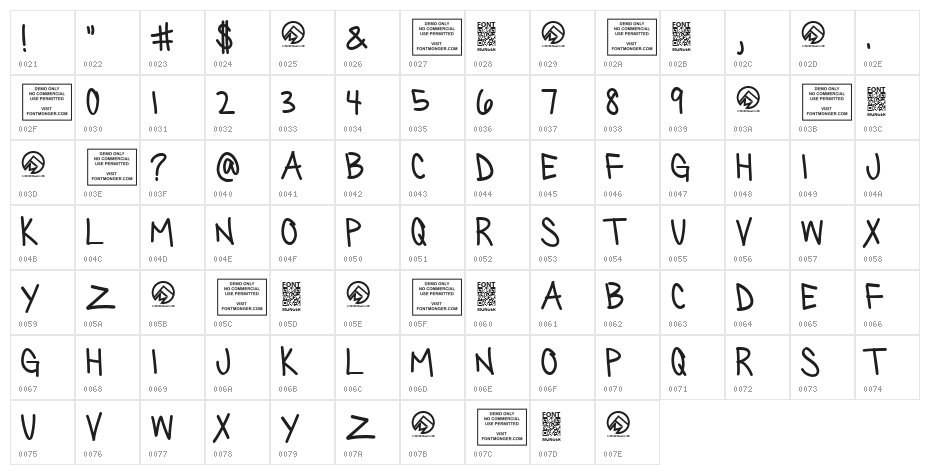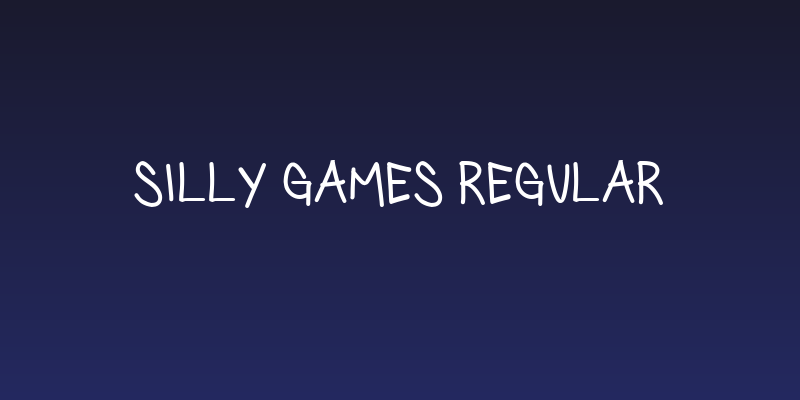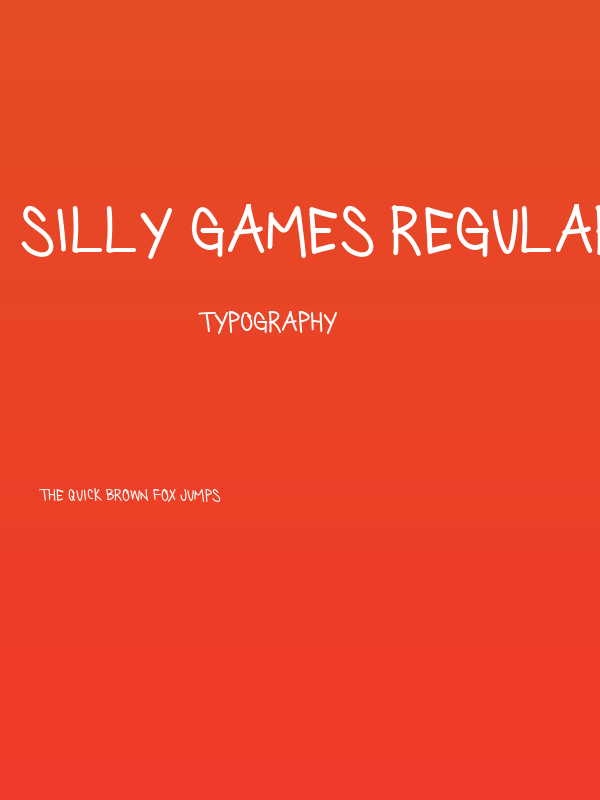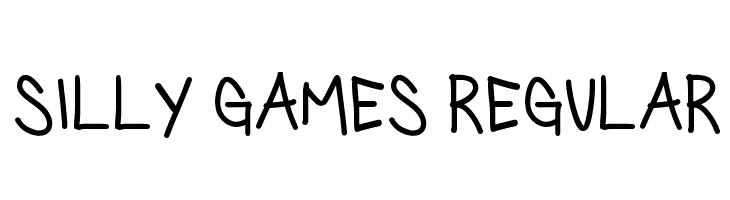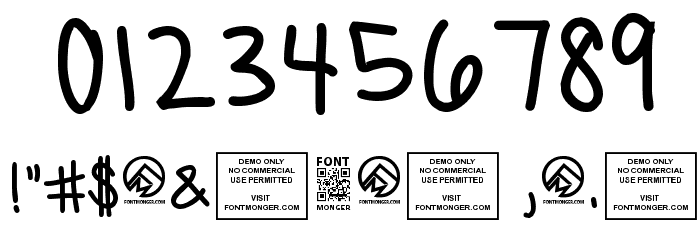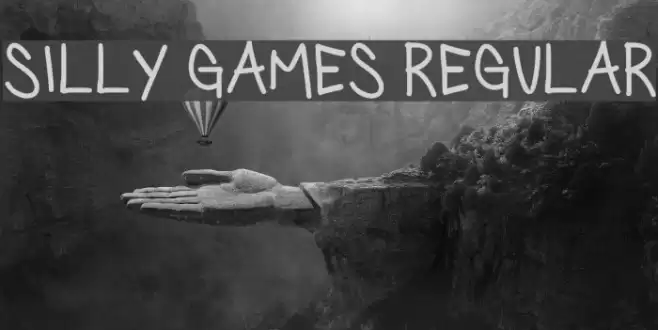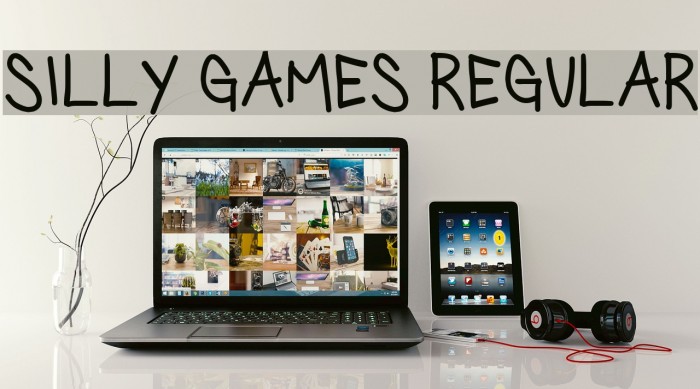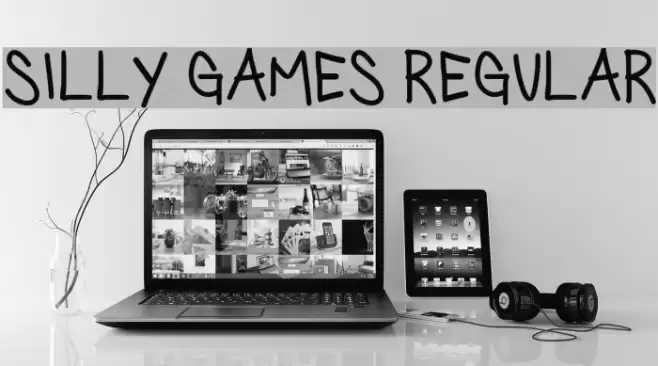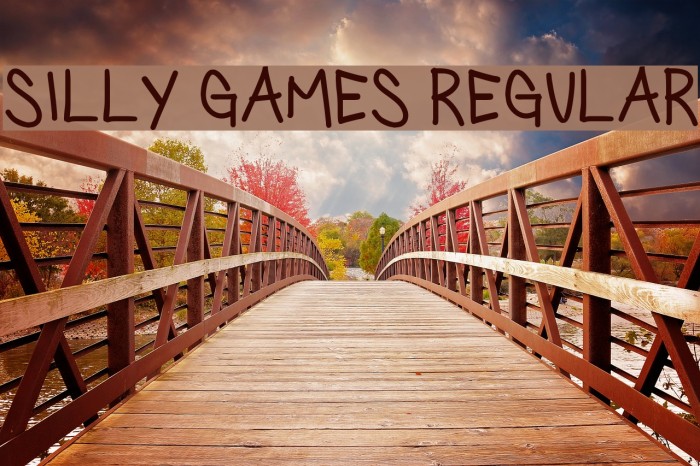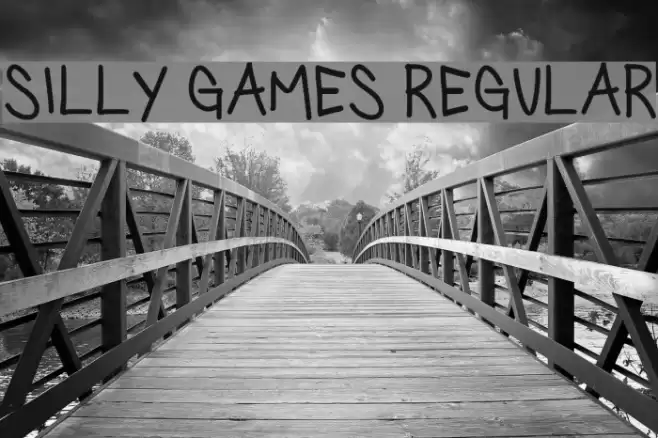
Silly Games Regular Font
| Gesamtstil | Playful |
| Vorgeschlagene Projekte | Ideal for children's books, playful branding, casual invitations, and creative posters. |